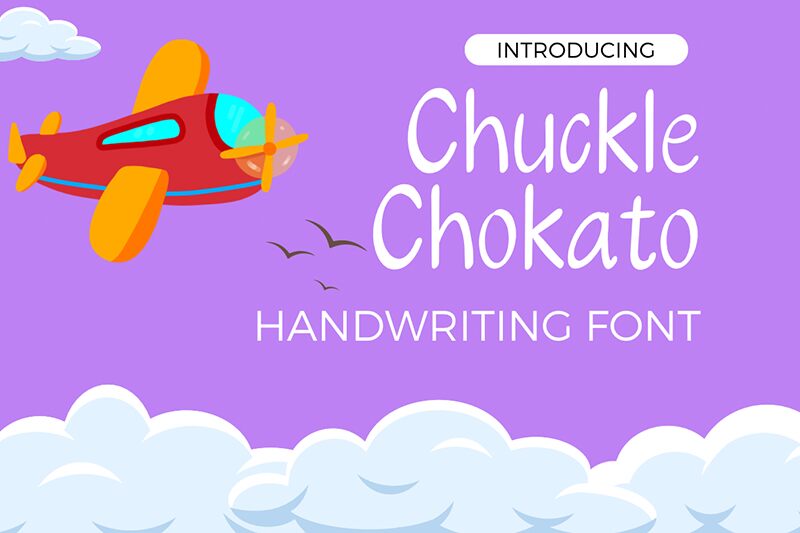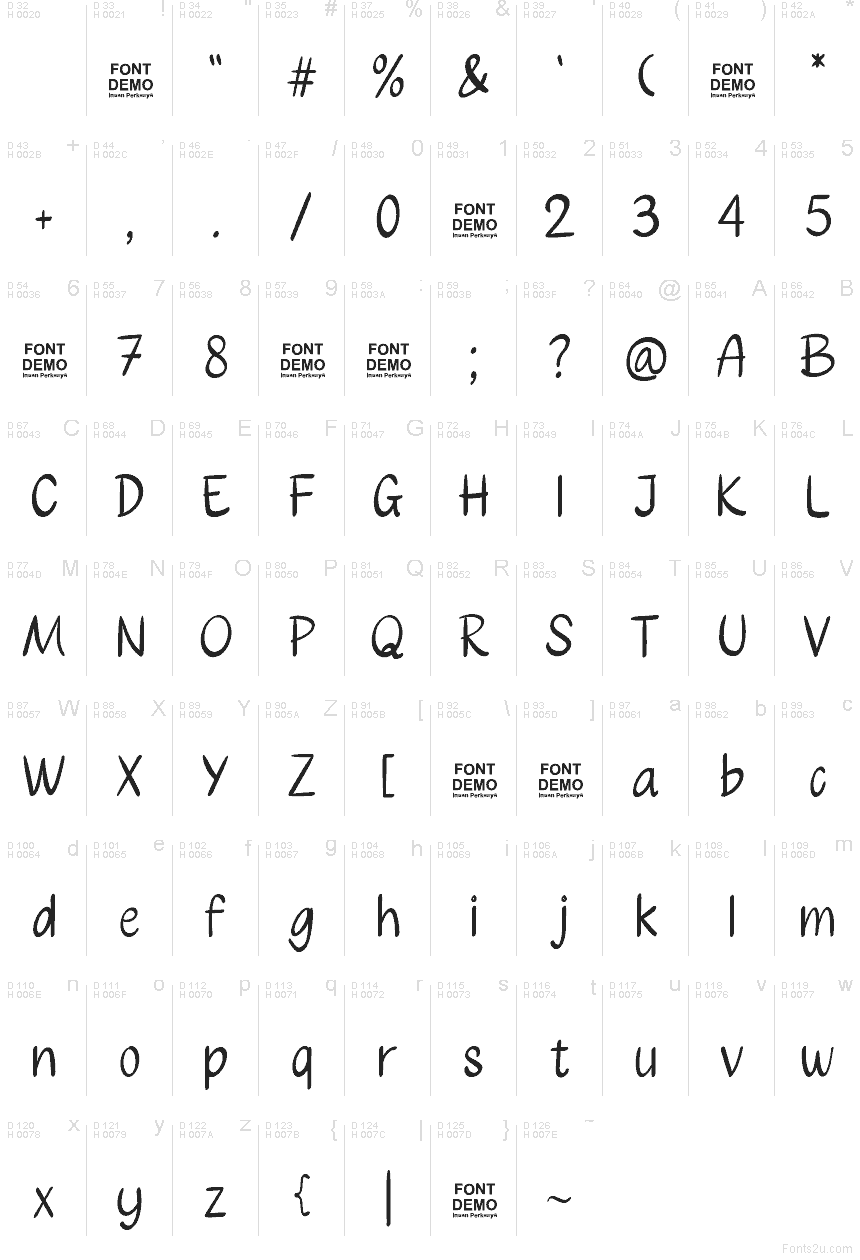
Chuckle Chokato
Шрифт Chuckle Chokato от Insan Perkasya — это бесплатный рукописный шрифт с высокими, непринужденными буквами и свободным, живым ритмом. Закругленные штрихи и слегка неровные формы придают ему дружелюбный, неформальный вид, не создавая ощущения беспорядочности.
Chuckle Chokato отлично подходит для открыток, детских проектов, крафтовой упаковки, публикаций в соцсетях и графики с цитатами, так как его рукописный стиль ощущается личным и расслабленным. Он также хорош для акцентов в логотипах, заметок на плакатах и повседневного брендинга, если вам нужен текст, который выглядит скорее набросанным от руки, чем напечатанным.